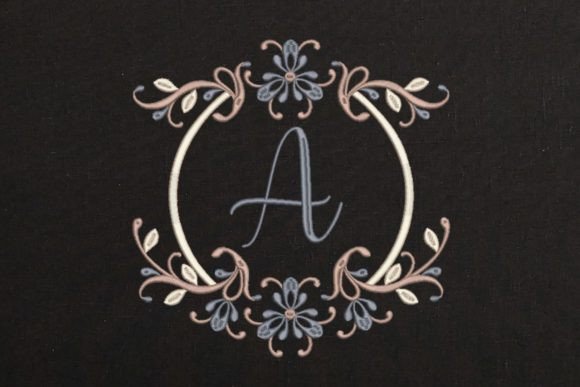
Single Monogram in Frame Letter a
適切なデザイン要素を見つけるのは難しい場合がありますが、Single Monogram in Frame Letter aは作品を即座に引き立てる優れたコレクションを提供します。
POD(オンデマンド印刷)製品、結婚式の招待状、またはソーシャルメディアのグラフィックを作成している場合でも、Single Monogram in Frame Letter aは理想的です。